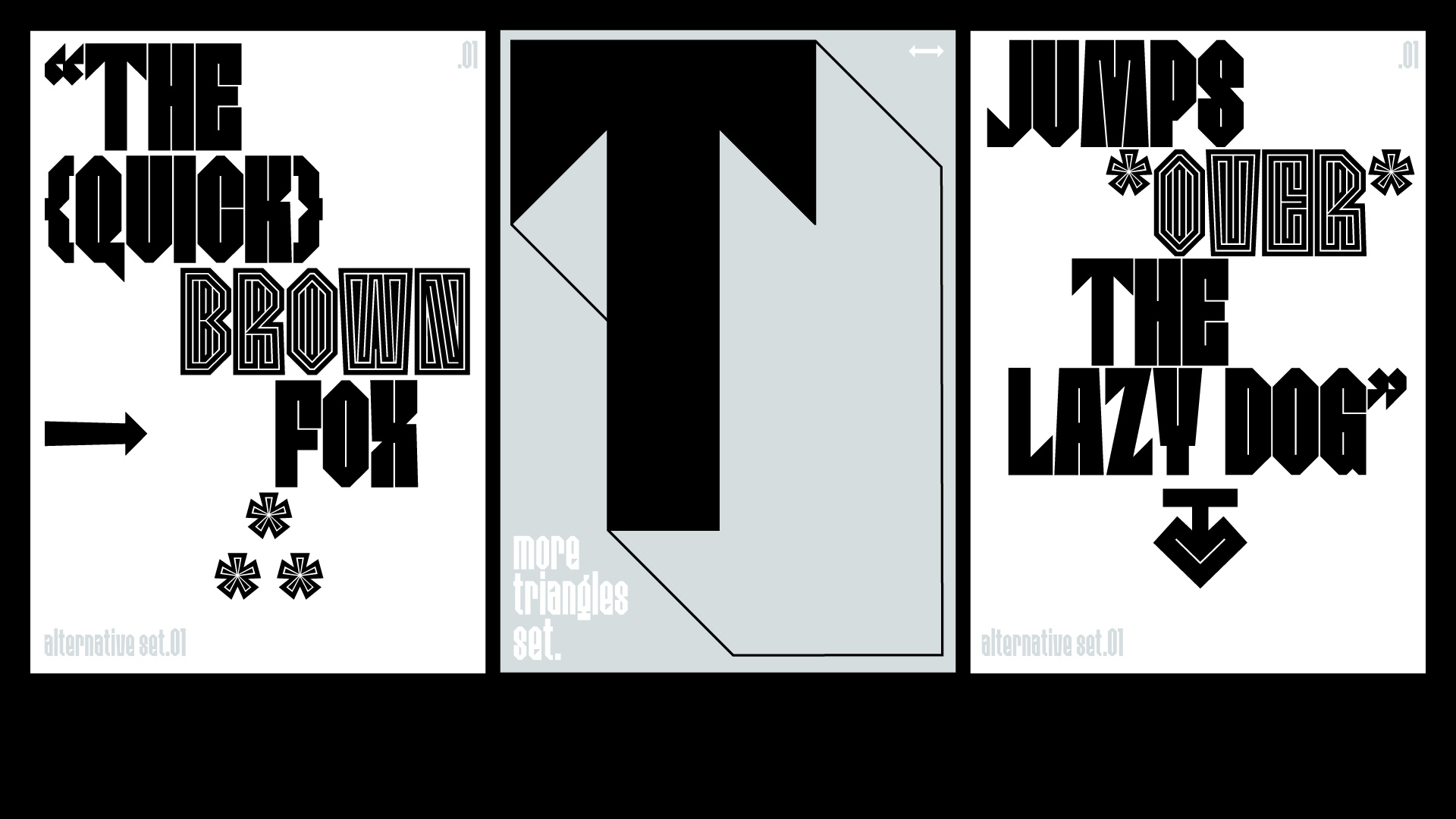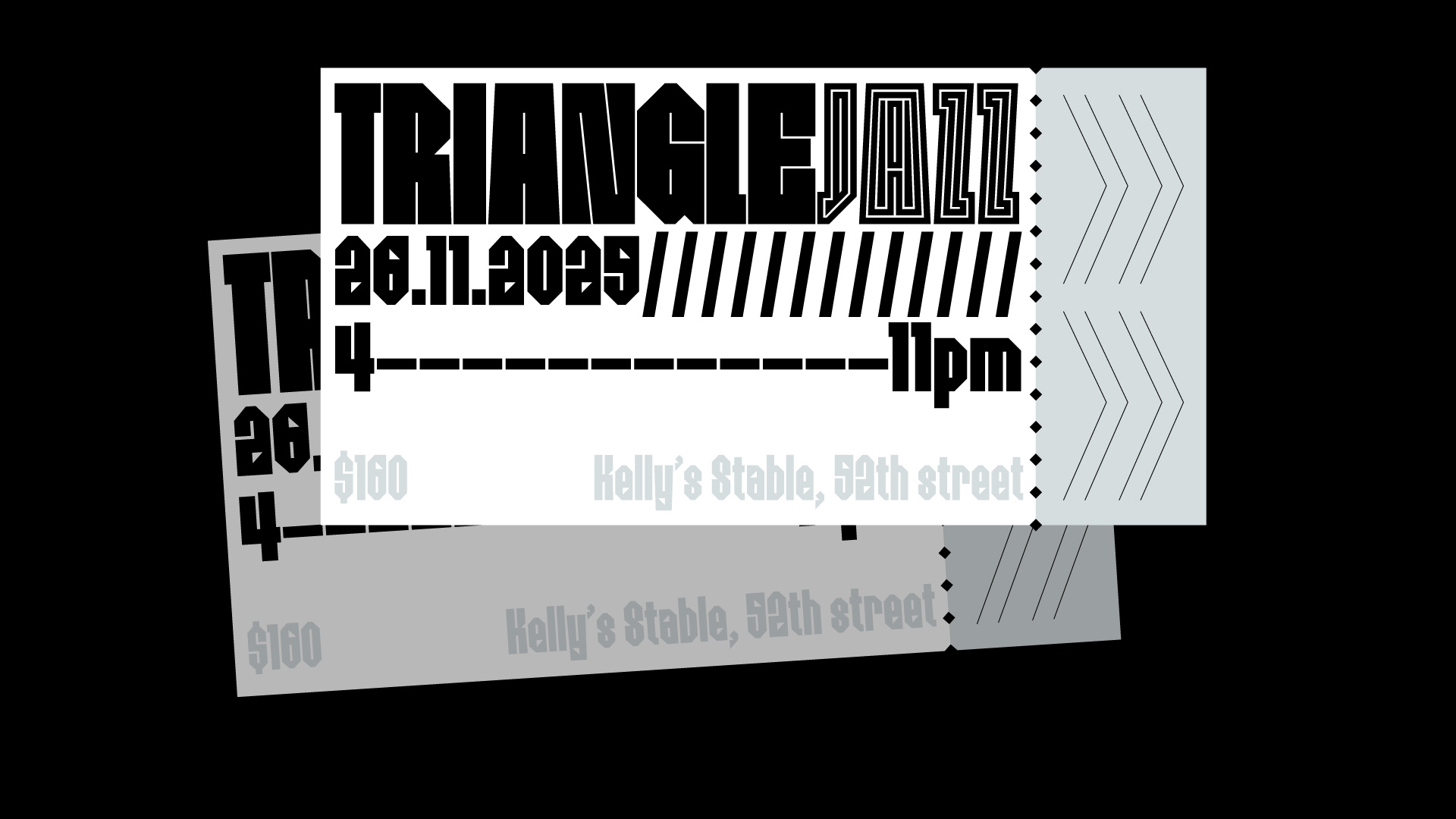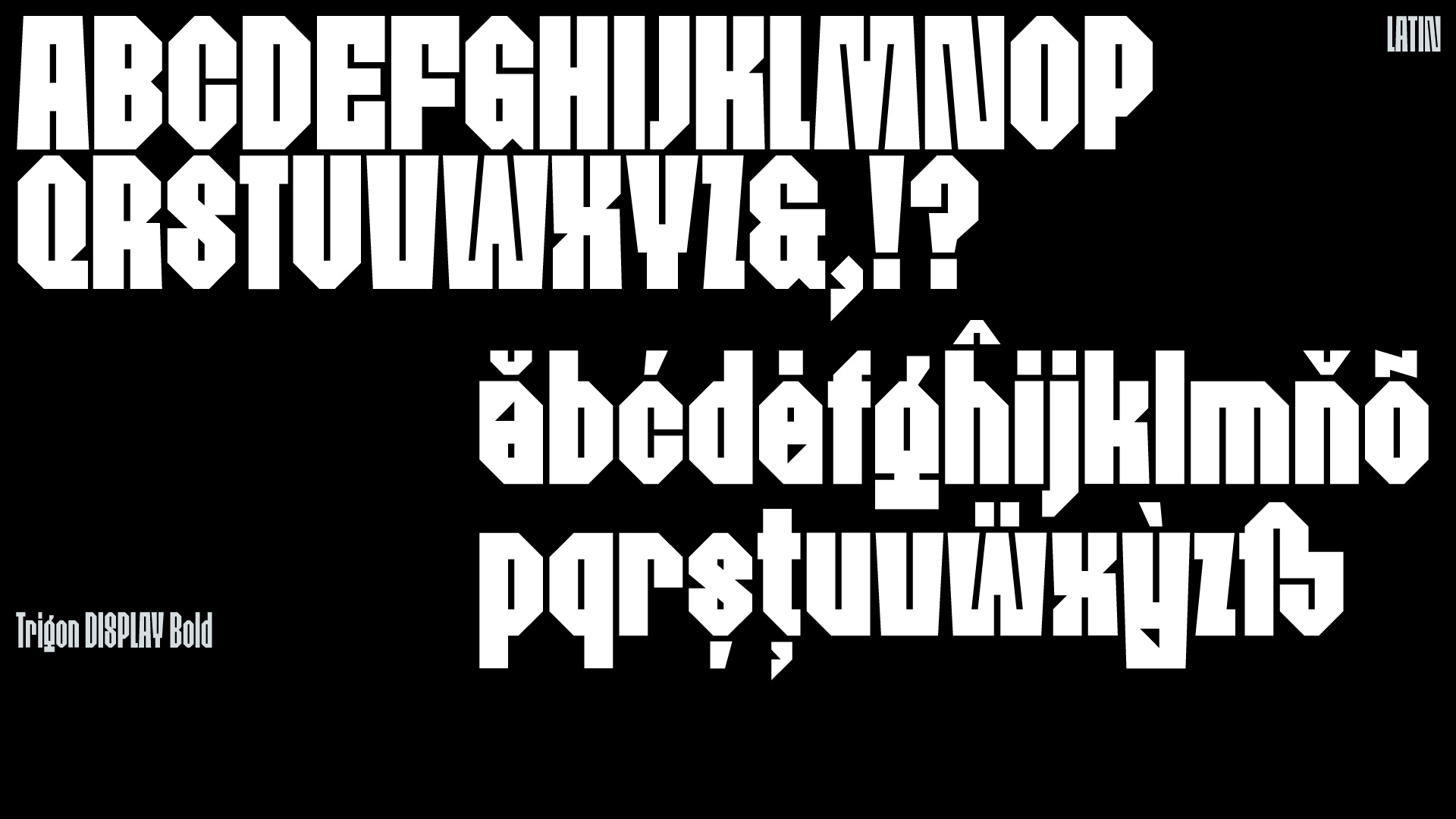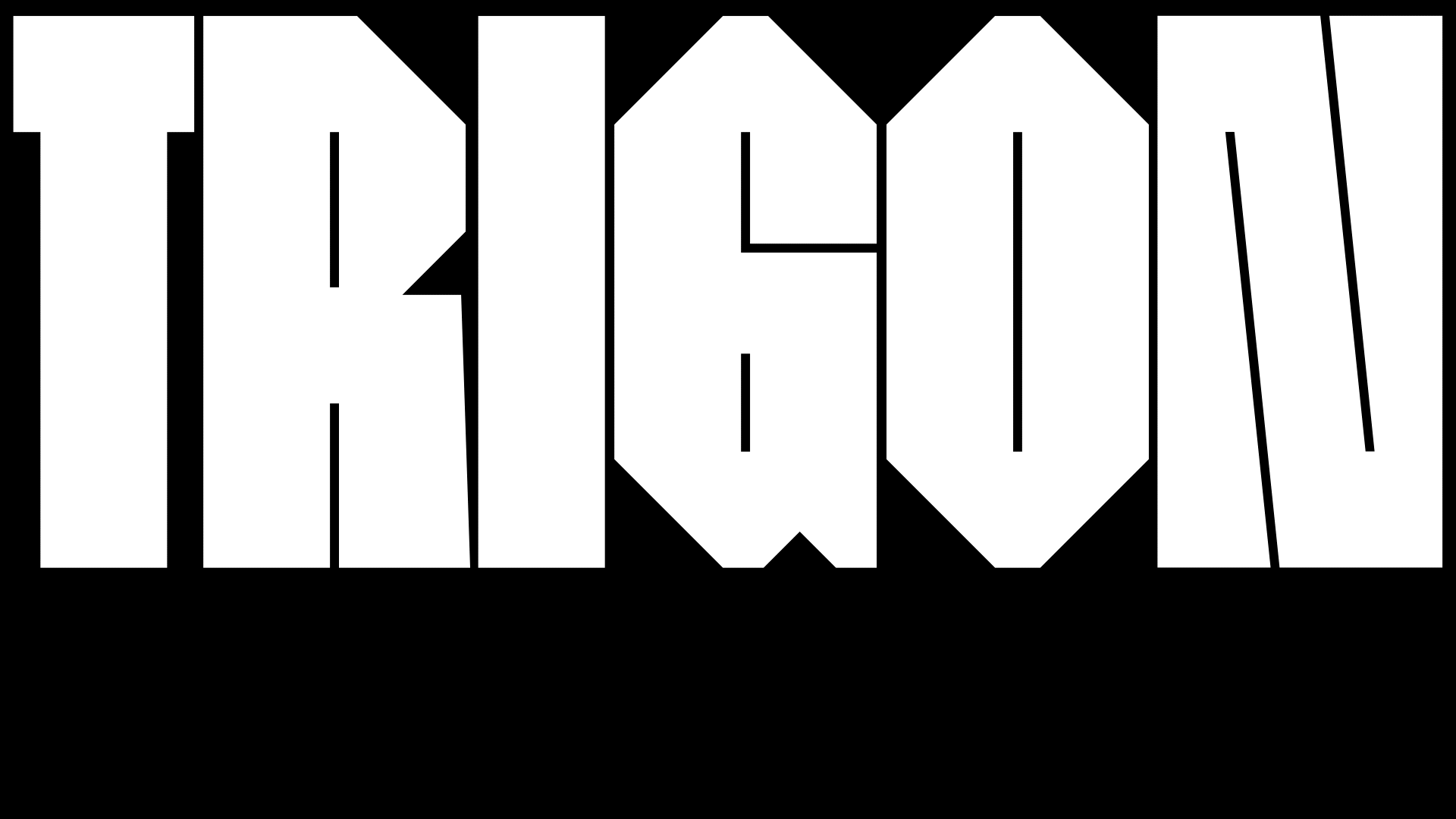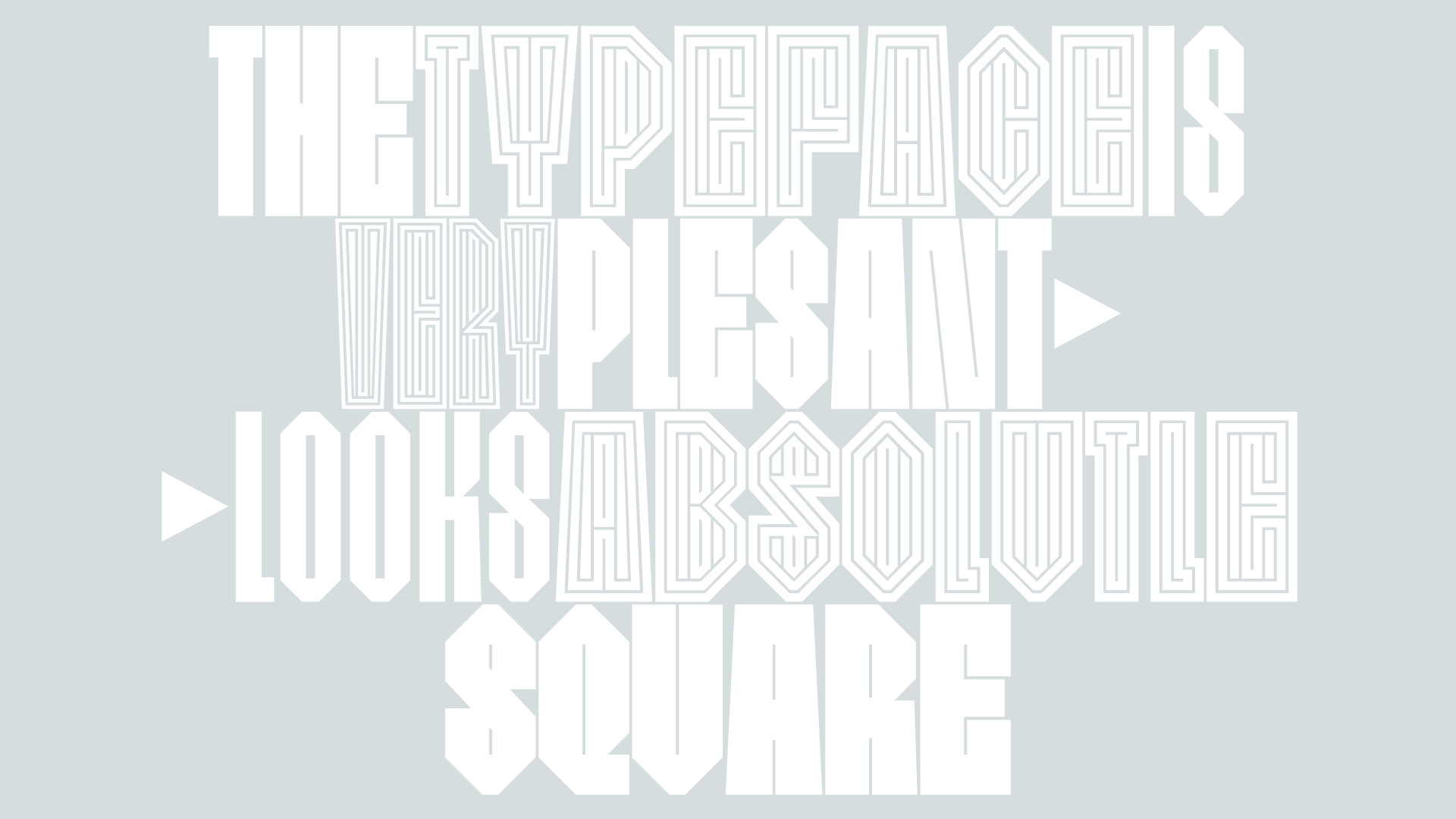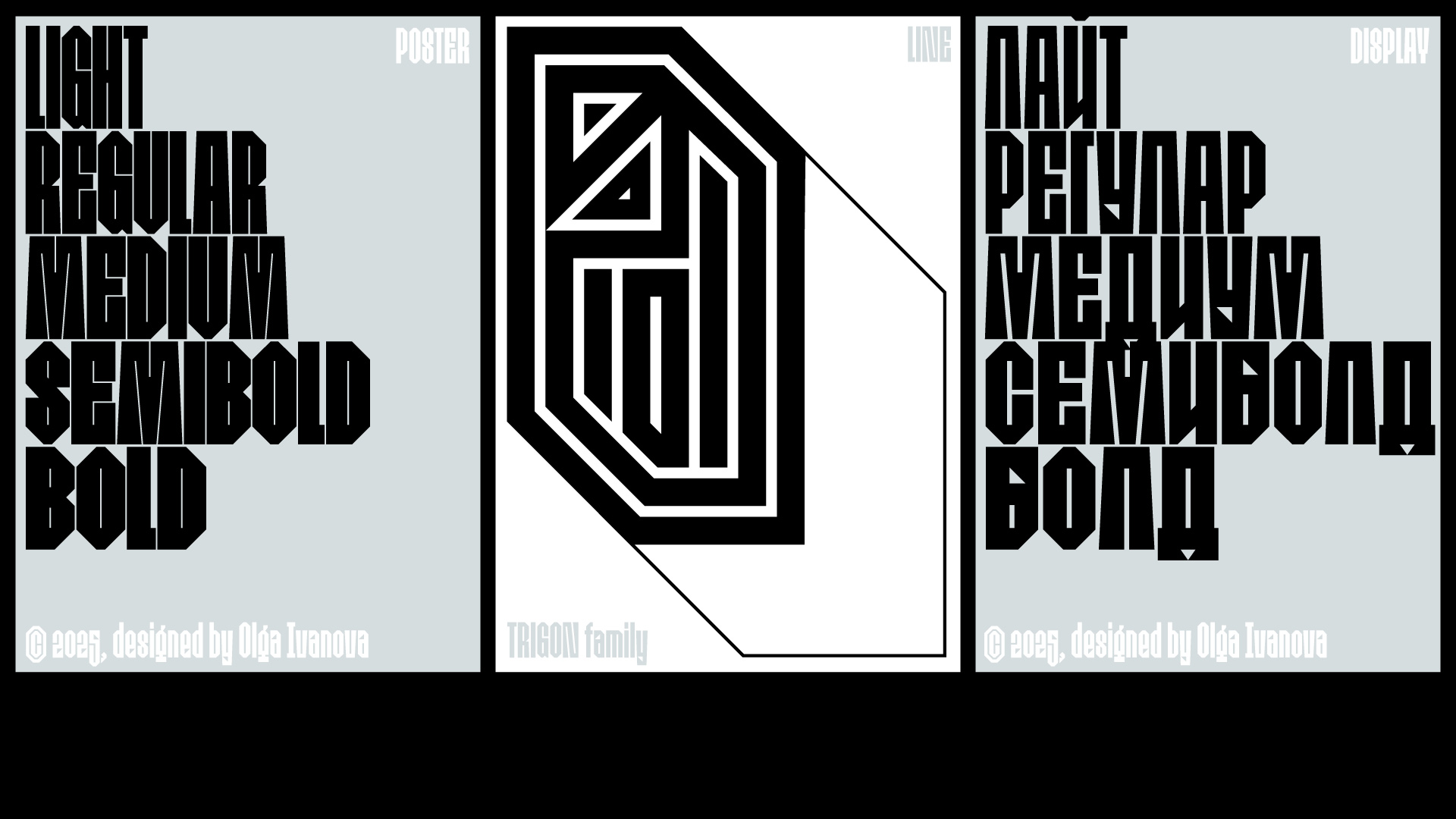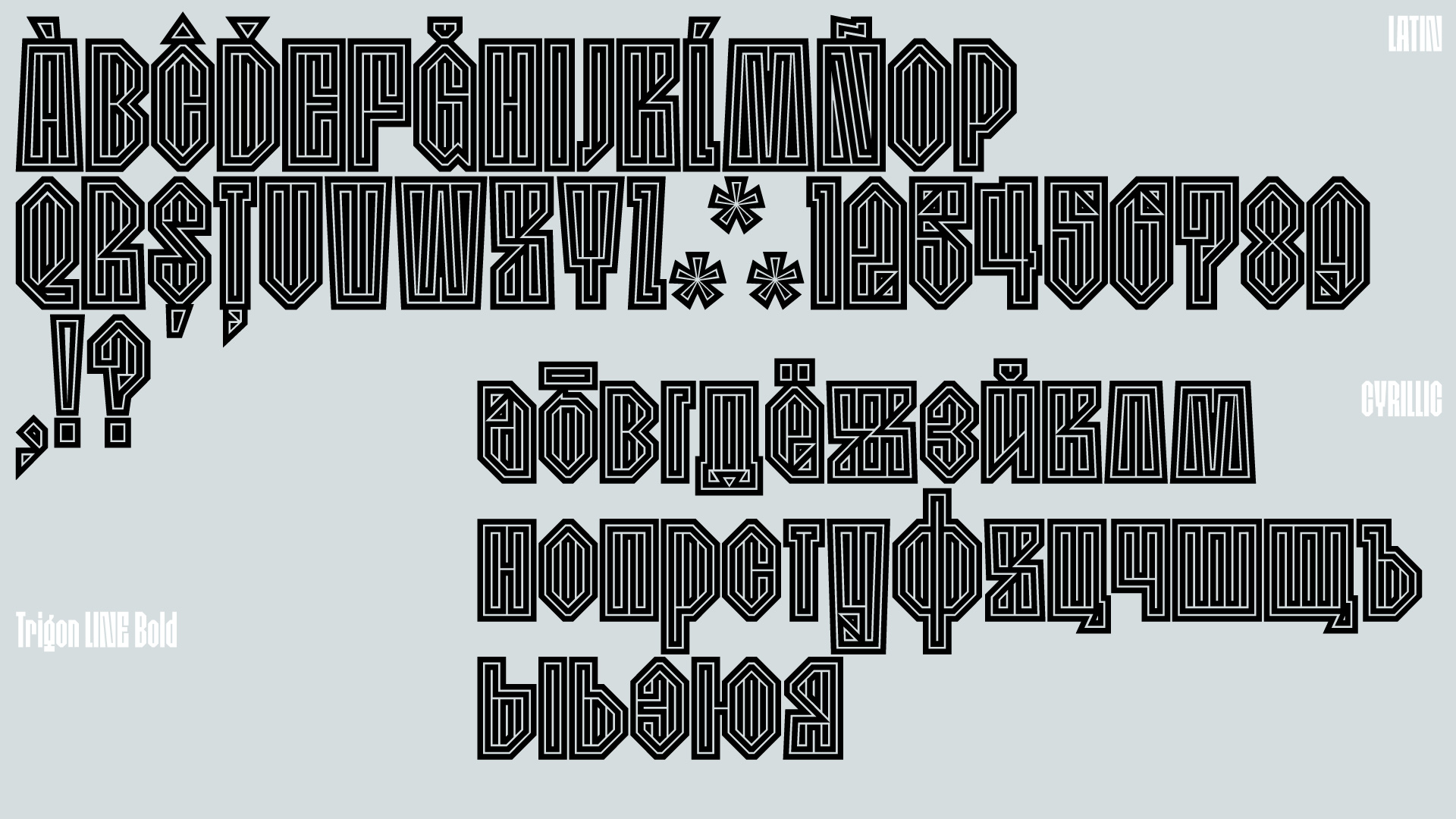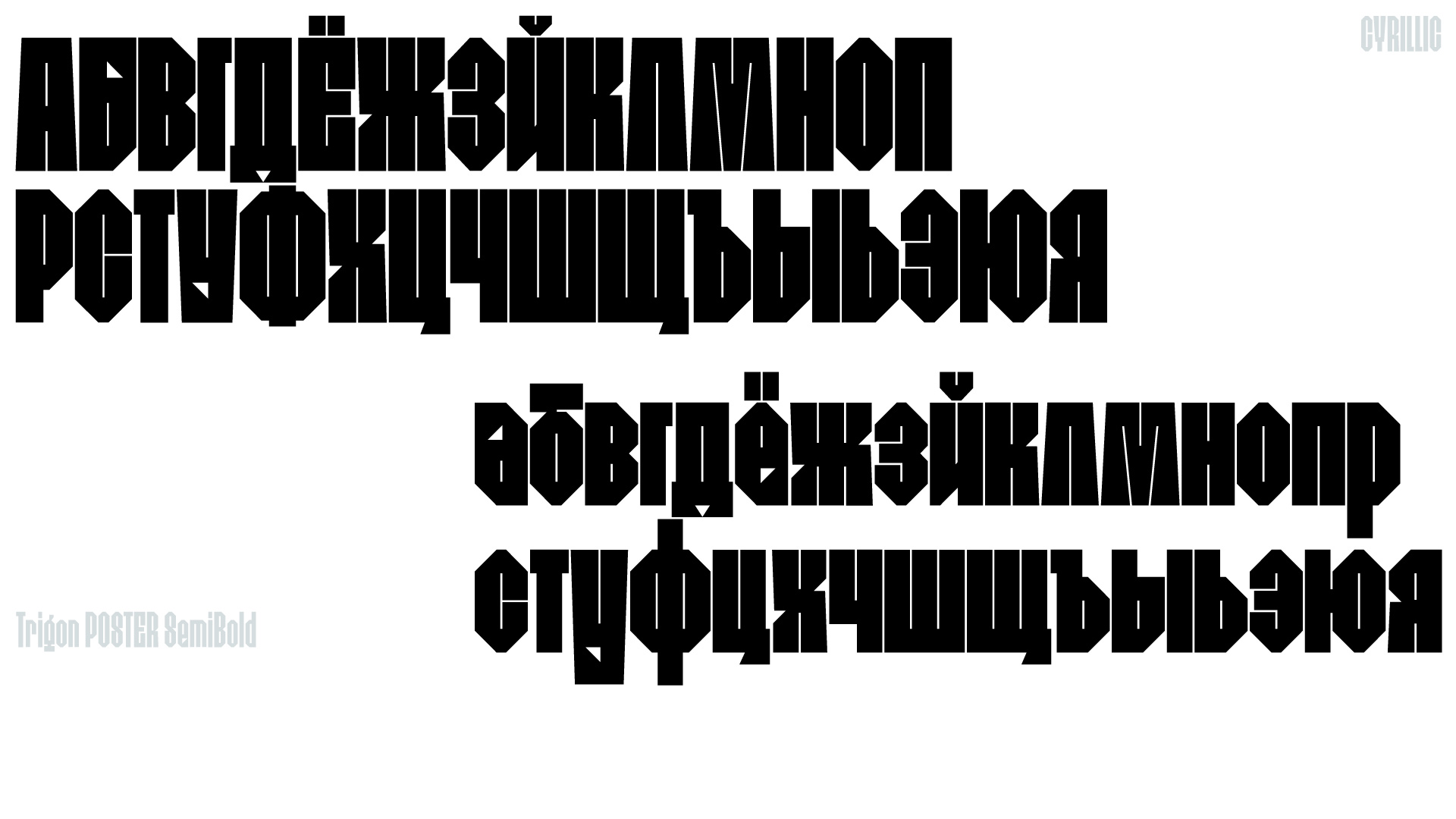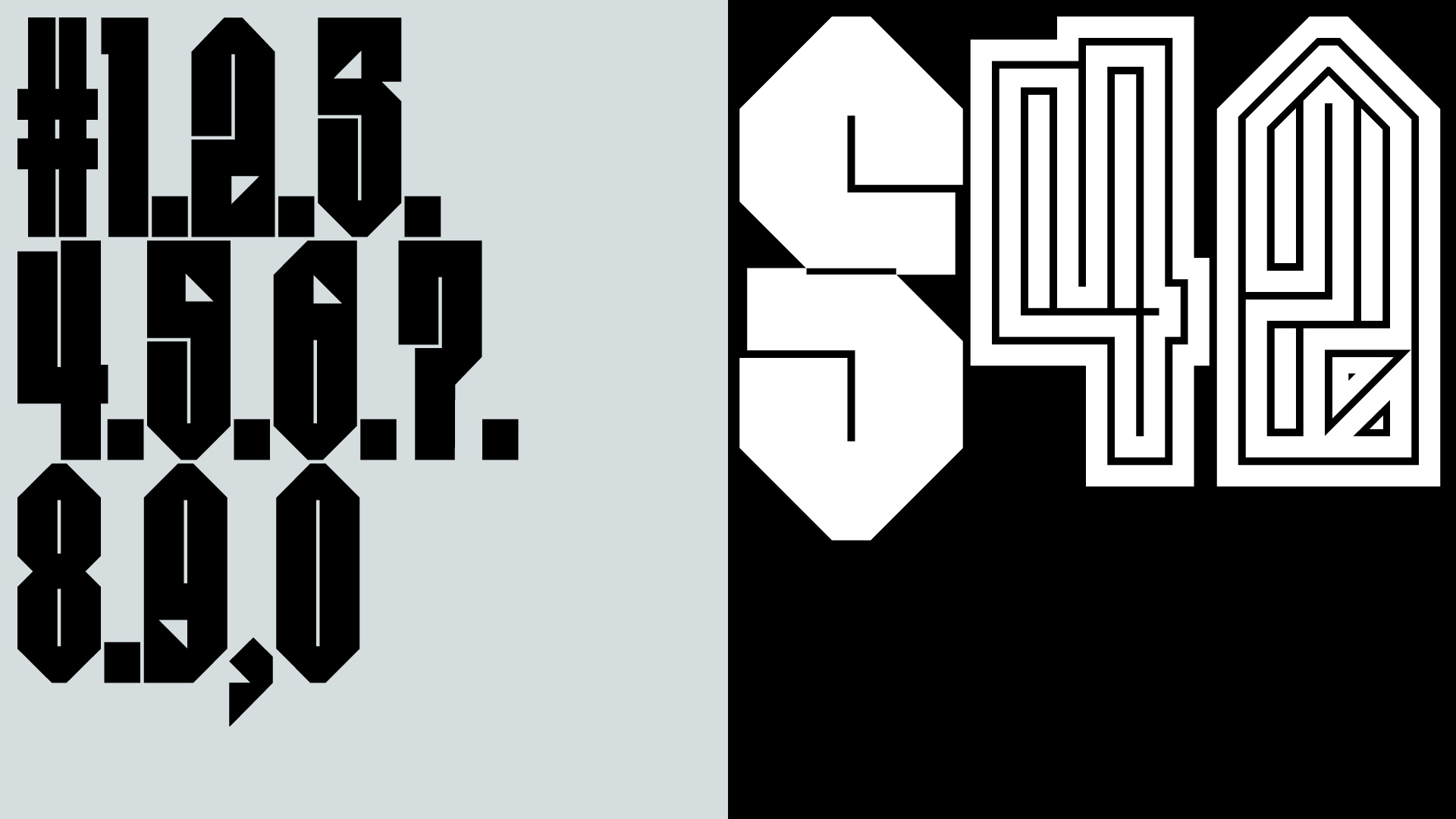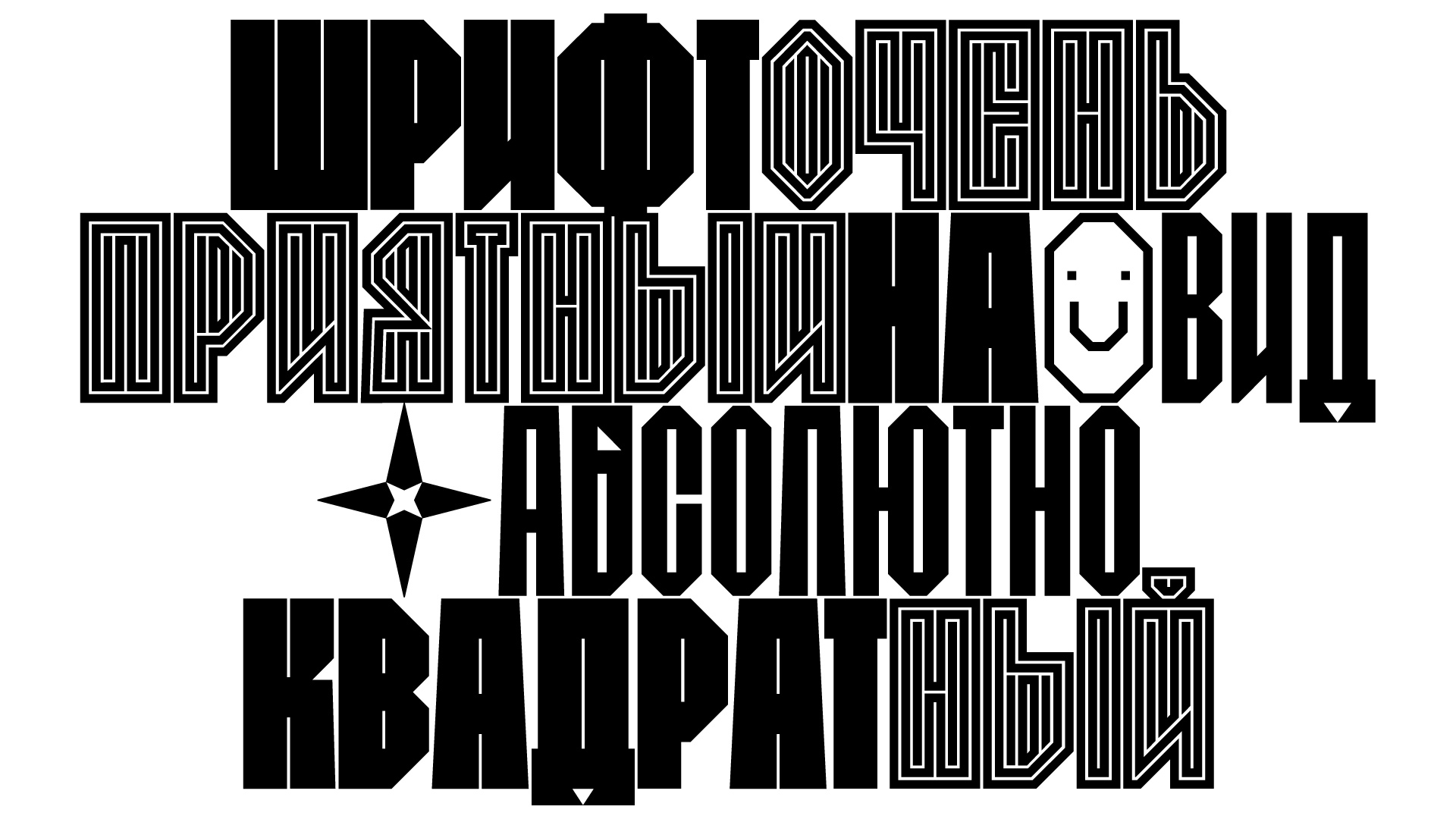
TRIGON
Trigon — геометрическая игра, основанная на палочном шрифте. При разработке акцент был сделан не только на форме линий, из которых строятся буквы, но и на внутреннем белом пространстве. Это сделало шрифт по-настоящему графичным. В результате появились характерные белые и чёрные треугольные формы, которые стали частью визуального языка Trigon.
В альтернативном сете More triangles некоторые знаки обретают массивные треугольные засечки, создавая уникальный ритм и характер.
Семейство шрифтов Trigon: Poster, Display и Line, — обладает простыми, чёткими формами и современным характером. В набор входят строчные и прописные буквы, а также 11 стилистических сетов, позволяющих адаптировать шрифт под разные задачи.